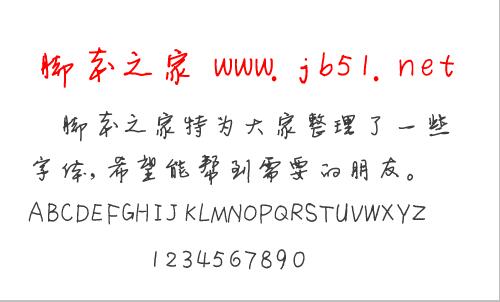
默陌秀麗體是一款非常不錯(cuò)的藝術(shù)字體,該字體給人一種非常大氣秀麗的感受,有一種清麗之美,同時(shí)字形連貫灑脫卻不失飄逸之風(fēng),是一款字形飄逸但不潦草,娟秀而不失大氣的鋼筆書(shū)法字體,有著非常出色的視覺(jué)感,給人堅(jiān)韌而細(xì)膩的視覺(jué)呈現(xiàn),如果有喜歡該字體的歡迎前來(lái)免費(fèi)下載收藏!